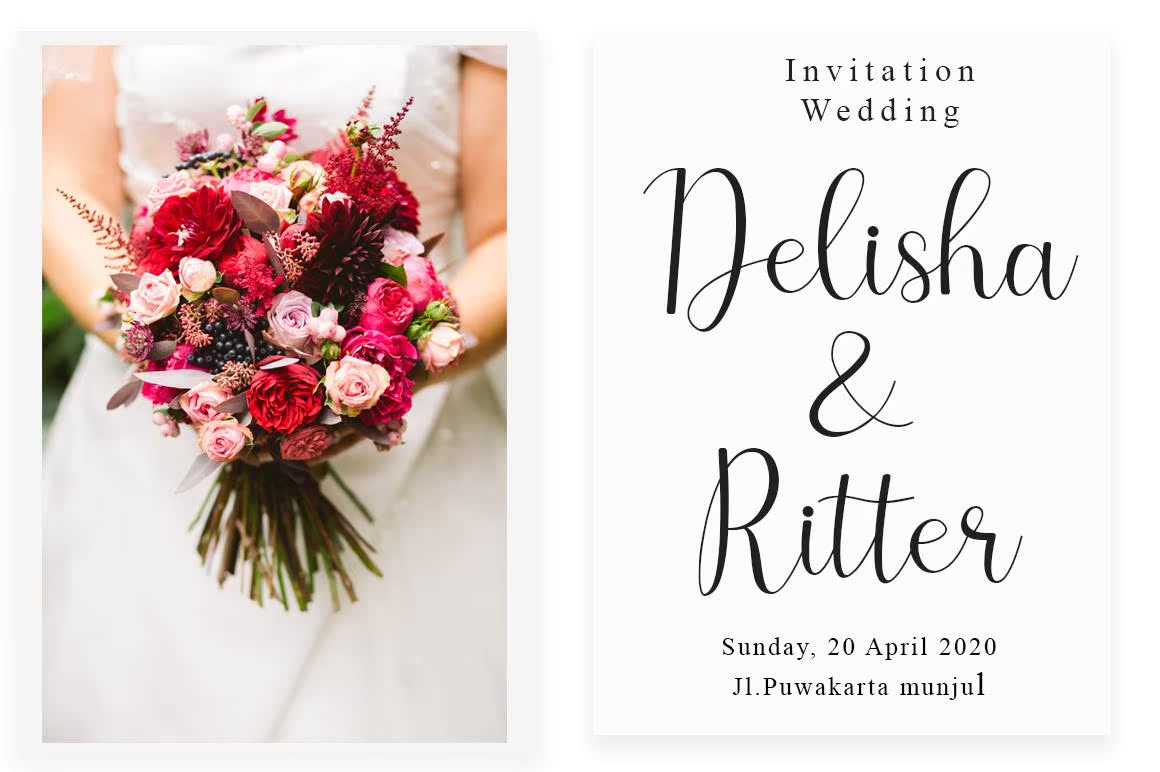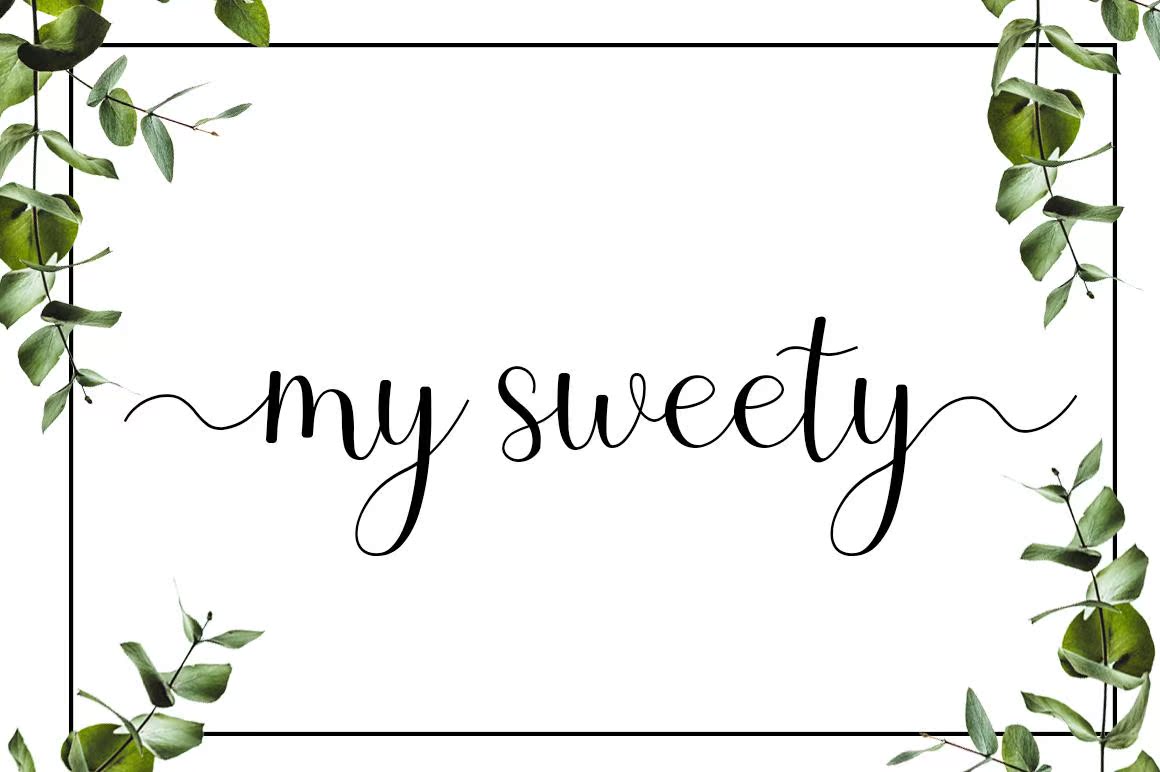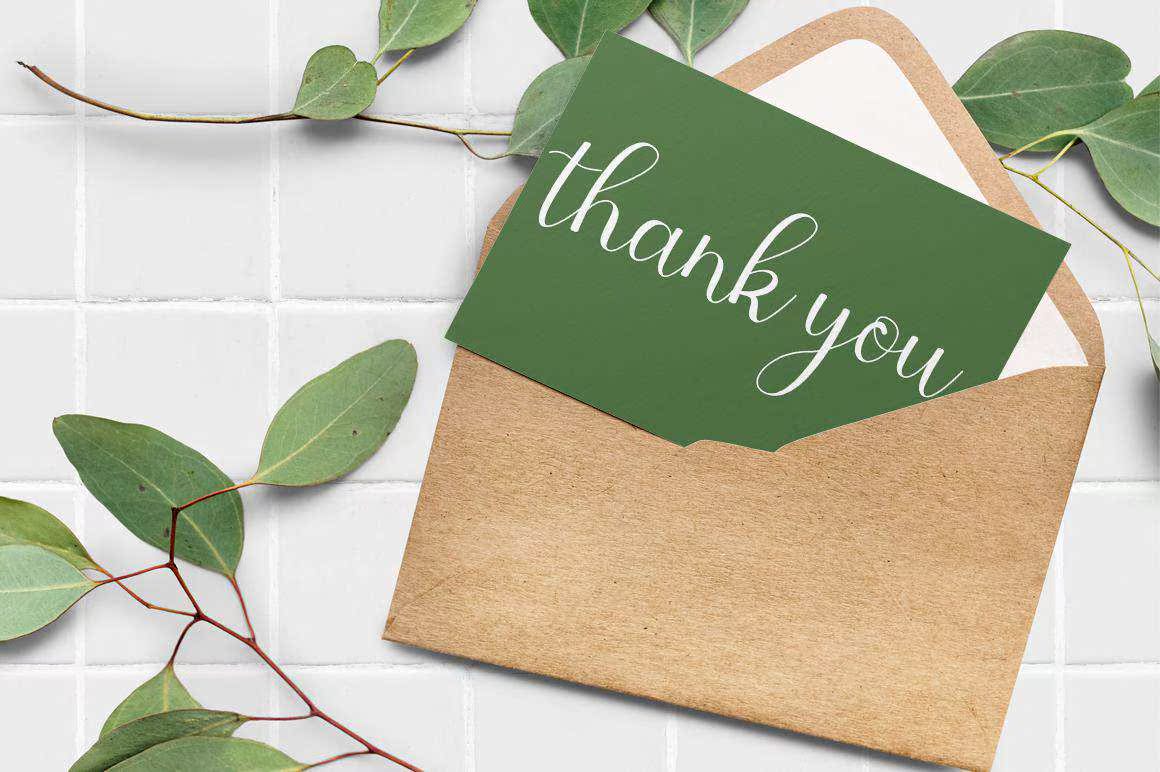
BELITHAMODERNSCRIPTFONT适用于商业卡、迎宾卡、邀请函、小报、QOUTS、LOGO、Colthing产品、商品和其他。BELITHAMODERNSCRIPTFONT适用于商业卡、迎宾卡、礼品卡和其他。BELITHAMODERNSCRIPTFONT适用于商业卡、迎宾卡,邀请牌、小报、qoutes、徽标、colthingproducts、商品和其他。